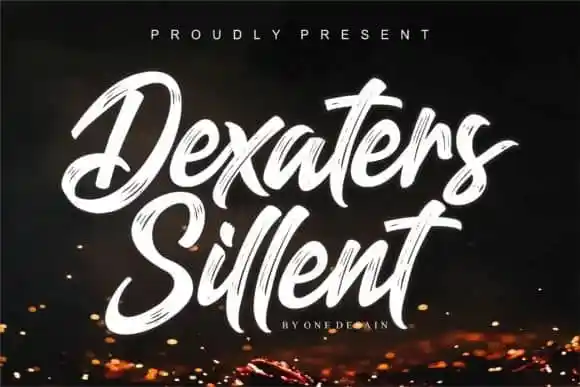
Dexaters Sillent Brush Font – Download Grátis
A Dexaters Sillent Brush Font é uma tipografia script com traços fortes que exibe um tom masculino intrínseco a ela. Criada pela One Desain, essa fonte foi desenhada com uma mão-dura e tempestuosa, oferecendo uma opção poderosa para projetos de marca, logotipia, posts nas redes sociais, anúncios, embalagens de produtos, design de produto, etiquetas e qualquer projeto que você possa estar lidando. É perfeitamente adequada para se destacar, seja através do seu próprio estilo marcante ou da sua forte identidade gráfica. Engane-se, esta fonte não é apenas uma opção, ela é um toque de unção para seus projetos mais exigentes.